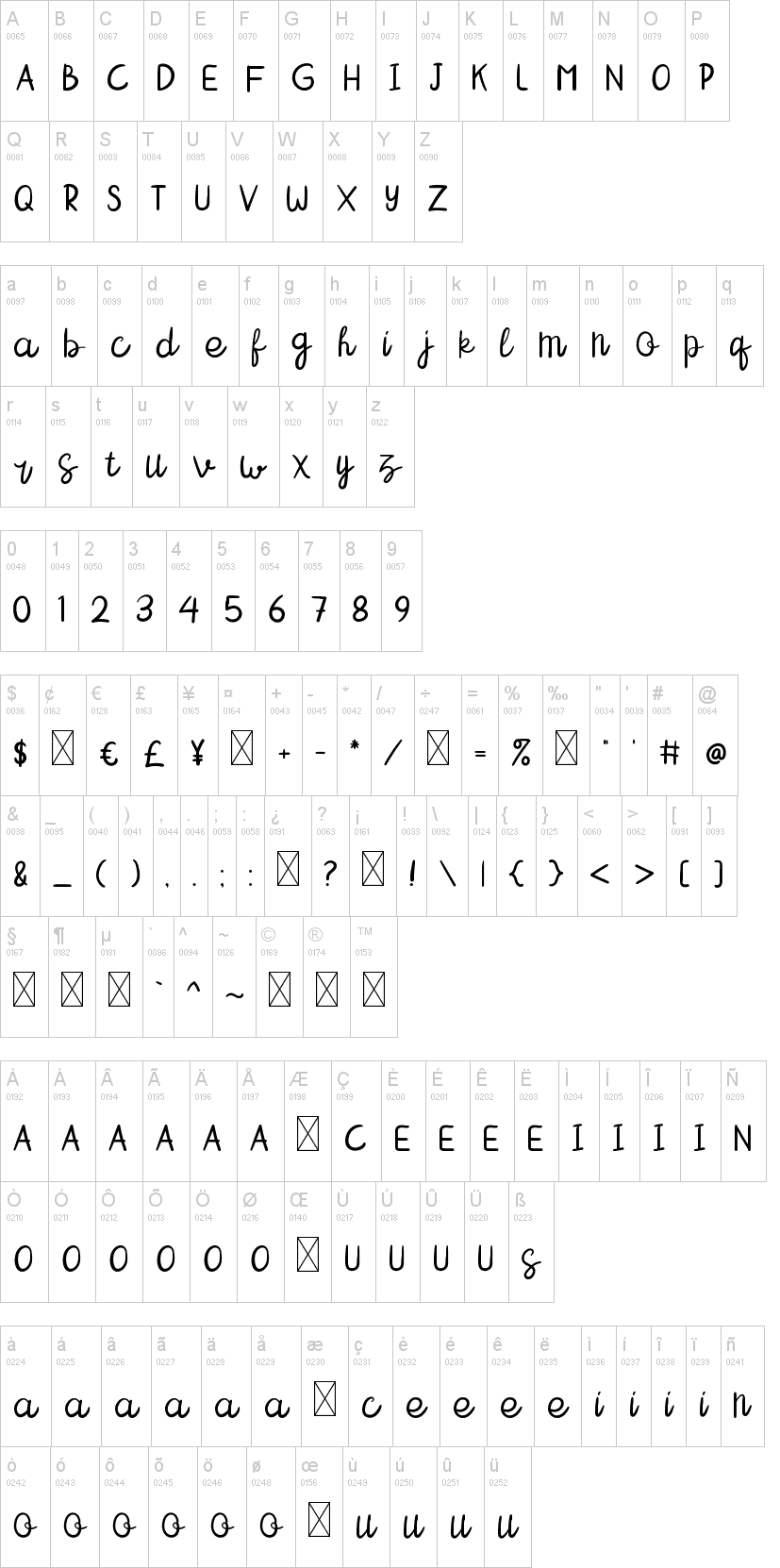
Thankful Sunday
Thankful Sunday 字体是一款温馨的手写字体,由美国设计师Cristina Pagnotta创作。它具有温暖的气息,细腻的笔触,柔和的线条,深沉的内涵,可以用于婚礼邀请函,祝福卡片,浪漫的爱情故事,以及温馨的春节等场景中。
Thankful Sunday是一款非常不错的手写艺术字体,具有很好的视觉感,适合于文化类的宣传设计、商业类品牌的广告和产品包装设计以及个性化文字排版等较多场景。
Thankful Sunday字符映射图